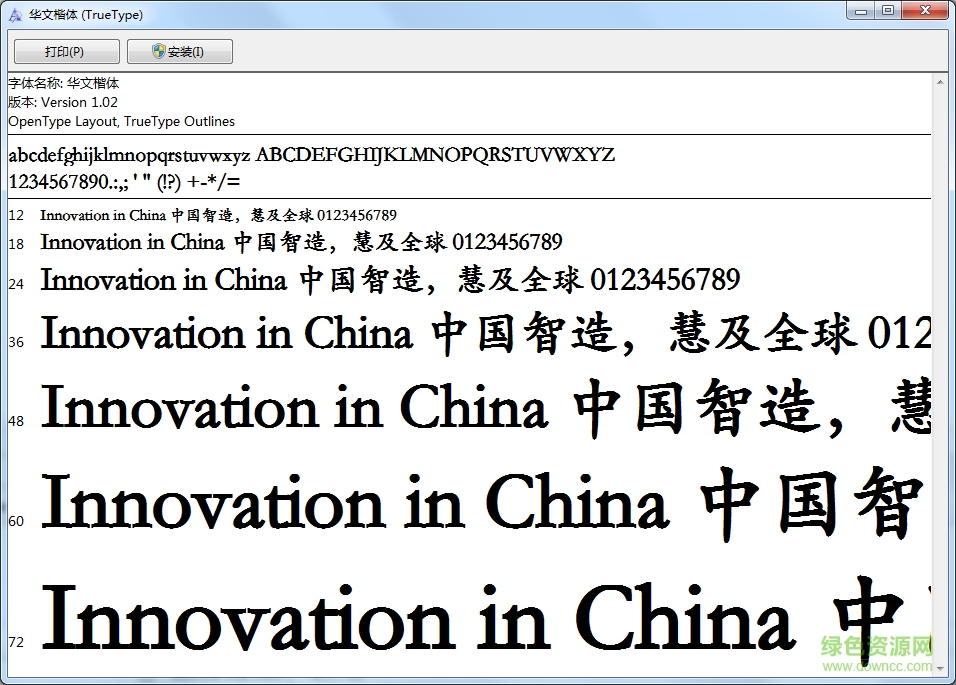
stkaiti-sc-bold字體
stkaiti-sc-bold是什么字體?stkaiti sc bold字體是一款加粗版的華文楷體,線(xiàn)條優(yōu)美,適用性強(qiáng),一般制作ppt或是文章排版時(shí)都用得上這款楷書(shū)字體,歡迎下載!
stkaiti-sc-bold字體